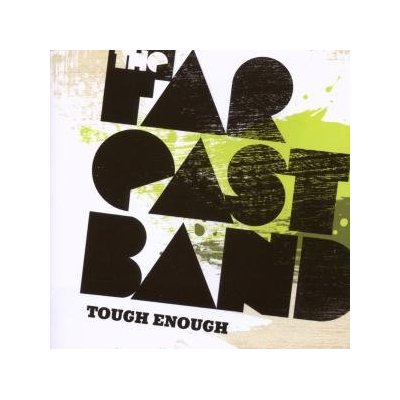
Suche Retro-Disco-Font (Beispiel included)
Hallo, kennt jemand ein paar Schriften die so aussehen wie diese hier im Beispiel. Es geht mir dabei jetzt nicht genau um diese abgebildete Schrift, es geht mir um den Stil dieser Schrift. Ich habe eine solche neulich in einem Buch meiner Professorin gesehen, allerdings erinnere ich mich nicht an den Namen der Schrift. Suche Namen und Bilder dazu. Wenn jemandem etwas einfällt immer her damit. :)
Die Mutter aller dieser Black-Schriften war sicherlich Baby Teeth von Milton Glaser*). Wurde meines Wissens aber noch nicht offiziell digitalisiert.
FattiPatti von Casady & Green ist eine Annäherung daran.
Ähnliches findest du z.B. auf identifont.com unter dem Stichwort Black Boton Bold.
*) For the records: Auf Paratype.com findet man eine cyrillische Babyteeth-Interpretation mit dem Namen Bebit.
Nachtrag: Wegen »Zur Zeit sehr angesagt« …